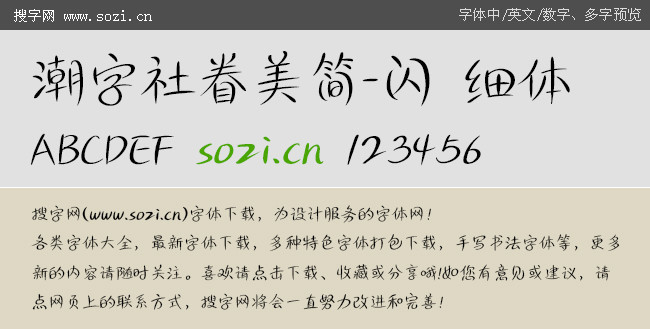
潮字社眷美簡-閃 細(xì)體
搜字網(wǎng)提供一款潮字社眷美簡-閃 細(xì)體中文字體下載,潮字社眷美體是一款線條優(yōu)美圓潤的藝術(shù)字體,風(fēng)格比一般的字體更有特色,連貫字跡顯得干練而不凌亂,清新簡明,具有很好的視覺感,適合應(yīng)用于藝術(shù)設(shè)計、平面宣傳設(shè)計、網(wǎng)頁設(shè)計等領(lǐng)域等應(yīng)用。(本字體為個人非商用版,商用請聯(lián)系作者購買授權(quán))